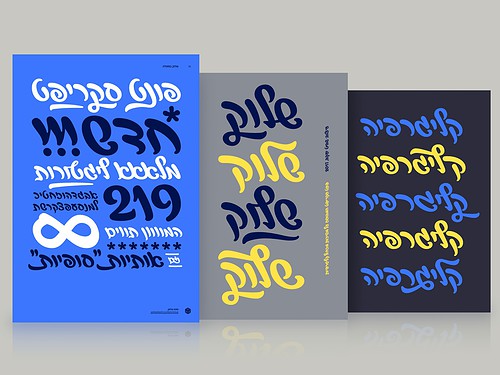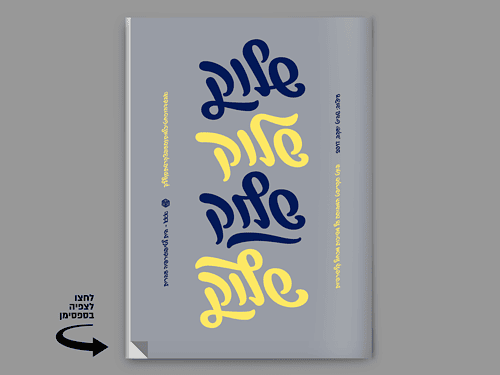
על אודות פונט שלוק
שלוק הוא פונט דו־לשוני מתוחכם ושמח שיכניס לעיצובים שלכם ימבה כיף! הוא פוּתח מתוך משיכות ידניות בטוש־מכחול קליגרפי יפני ושואב השראה מאותיות רהוטות נוסטלגיות. לאותיות הבסיס בעברית ובאנגלית פותחו וריאציות נוספות ונועזות, אותיות ״סופיות״, סוושים להדגשה, וכמות רצינית של ליגטורות - מה שמסתכם ב־640 תווים (!). מומלץ להשתמש בו ללוגואים מלאי־חיים ולכותרות מרעננות.
- ליגטורות שלום ← שלום
- Office ← Office
- אל אלף אש טו טי לו לי לל למ
- לף לץ עץ עע צא של אאא אש וגם
- ff ffi ffl fi fl ft st !!!
- סוואשים לקטוז ← לקטוז
- ן ל ך ג ט נ
- ABGHKLMNORSVWY
- j x z k g b l f y
- חלופות הקשריות מיובש ← מיובש
- חלופות סגנוניות ל ל ל ל ל ל ל
- א ג ו ז י מ נ ע פ ף צ ץ ת
- A B D H J K M P R S U Y
- ע ג B S H H ג נ ת ת ן
- f k l t u ! ₪ | &
- "אותיות סופיות" אילת ← אילת
- ב ד ה ע ק ר ש